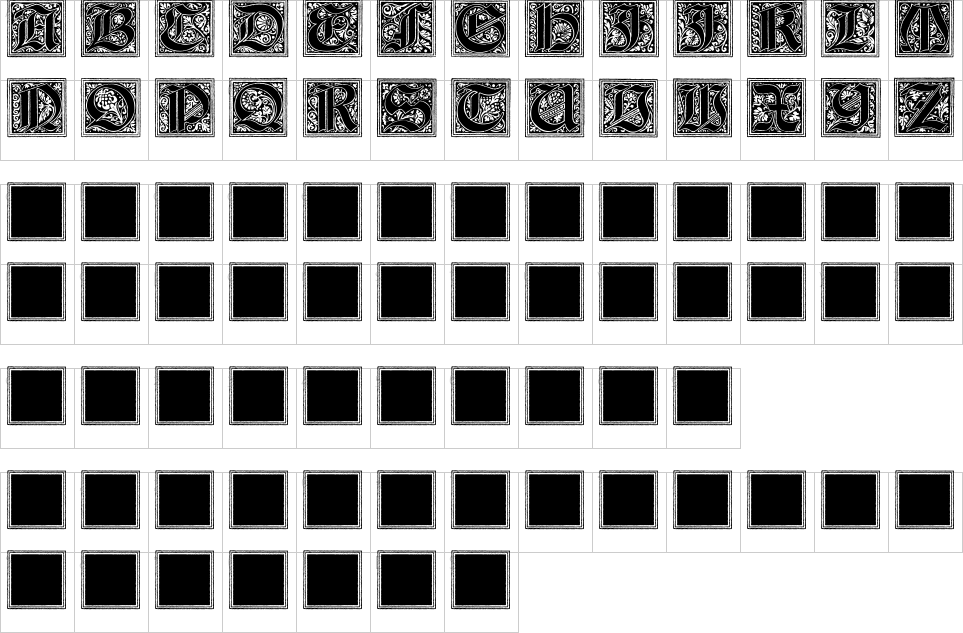
Descubra a elegância da Camelot Font para projetos digitais no seu Windows ou Mac. Desenhada por Paul Lloyd, esta bela fonte tem sido descarregada mais de 7.888 vezes. Com sua graciosidade e sutileza, ela se destaca como uma opção perfeita para criar textos atraentes e profissionais em seu próximo projeto visual. Seja você um designer ou um amante do design, o Camelot Font é certamente o elemento adicional que dará vida à sua criação. Não deixe de experimentar essa fonte gratuita hoje!